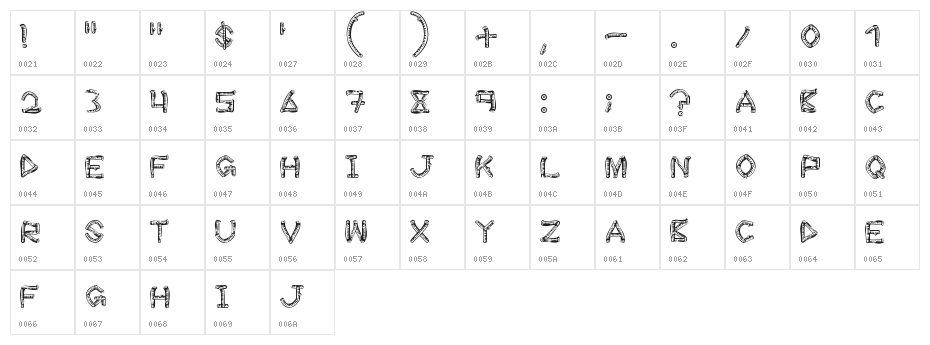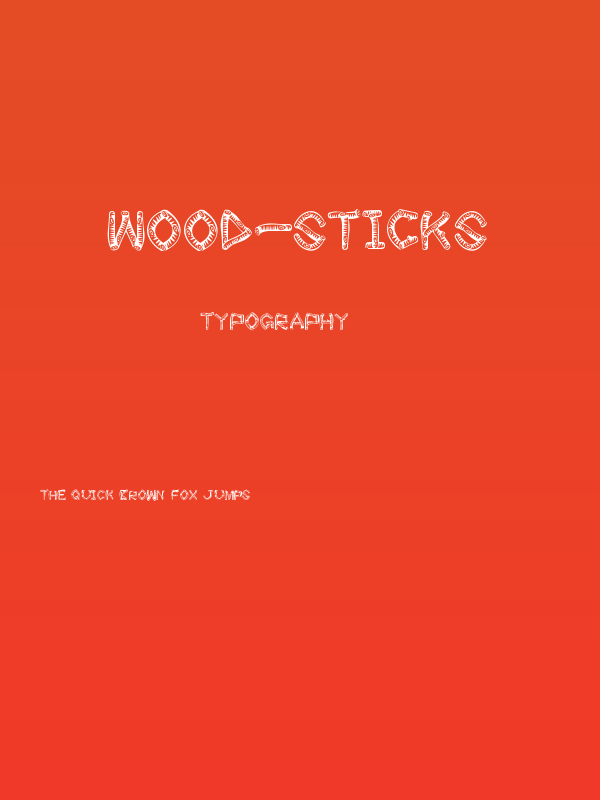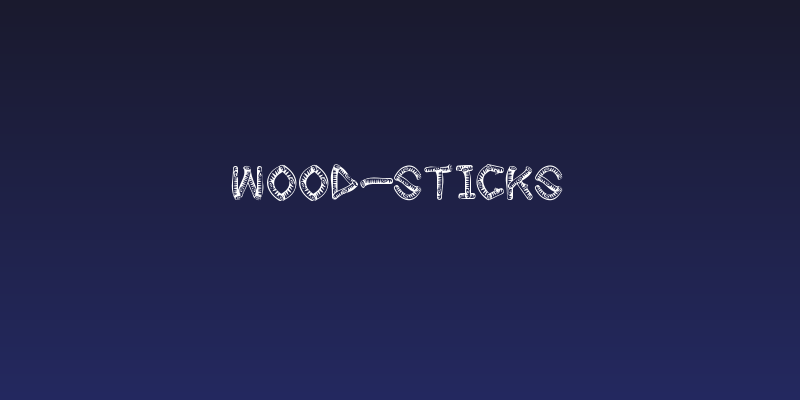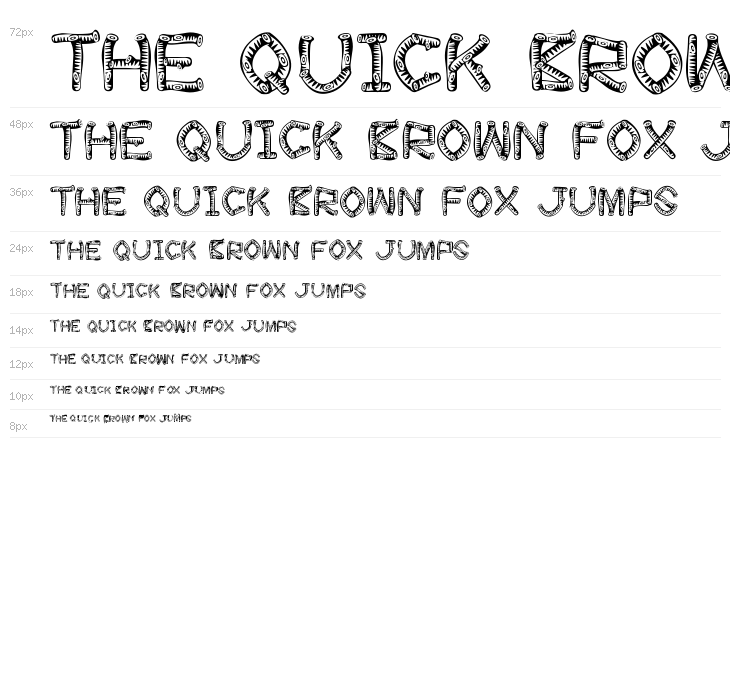
wood-sticks Font
✎ Decorative
| 分类 | Decorative |
| 使用场景 | Logos, Headlines, Posters |
| 推荐项目 | Ideal for nature-themed posters, children's book covers, outdoor event invitations, and eco-friendly product branding. |